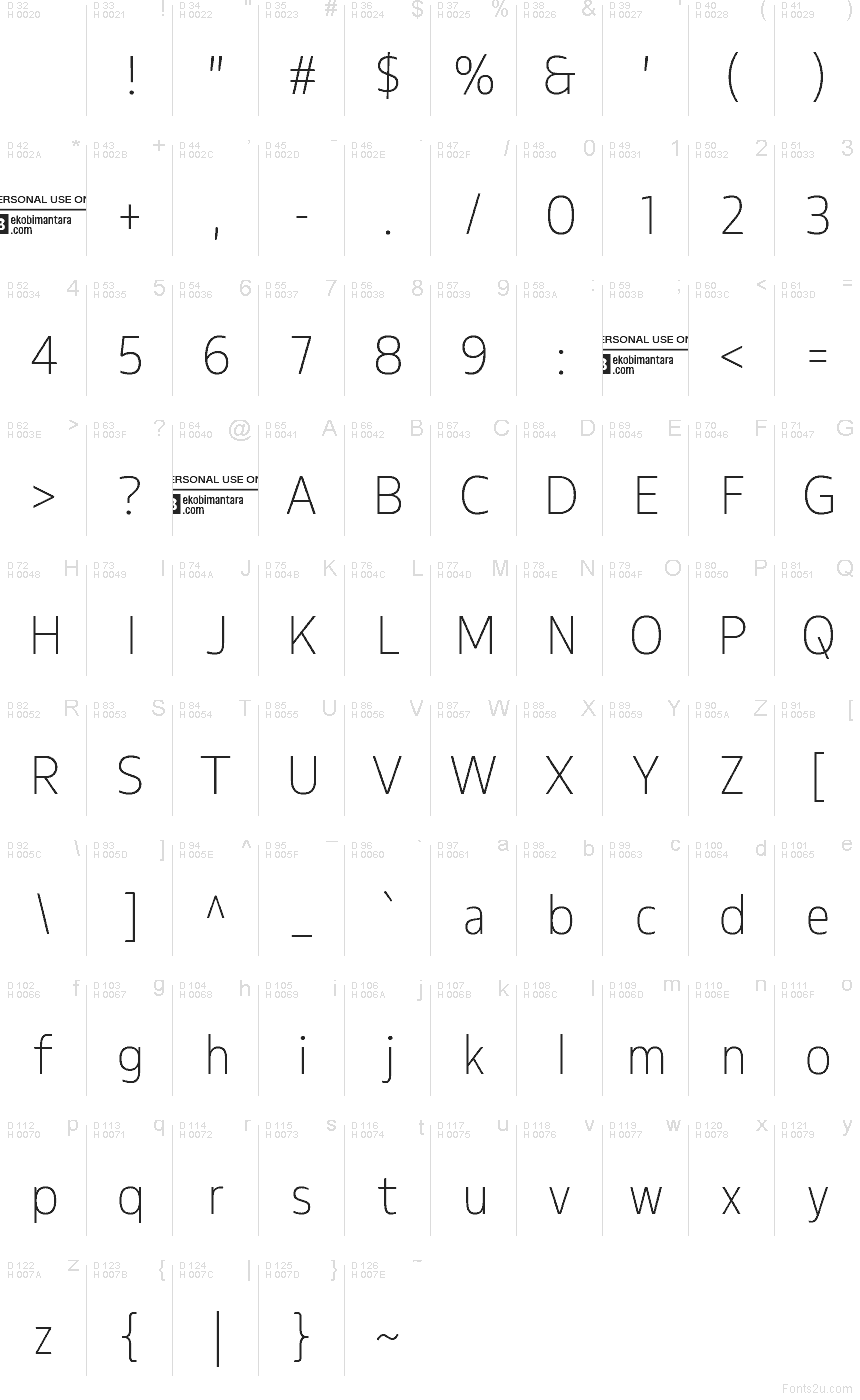
Profa Thin Condensed, créée par Eko Bimantara, est une police linéale gratuite, fine et étroite, avec un style moderniste épuré. Ses caractères donnent une impression de légèreté et de droiture, avec des proportions étroites, des formes arrondies fluides et un rythme élancé qui confère à cette police une élégance aérienne plutôt qu'une allure austère.
Elle s'intègre naturellement dans l'identité visuelle de marques de mode, les affiches d'exposition, les couvertures de magazines, les titres et les packagings où une touche d'élégance verticale fait toute la différence. En tant que police gratuite, elle est idéale pour les titres courts, les logos et les citations éditoriales, surtout lorsque vous recherchez une note géométrique douce sans la lourdeur d'une linéale plus épaisse.